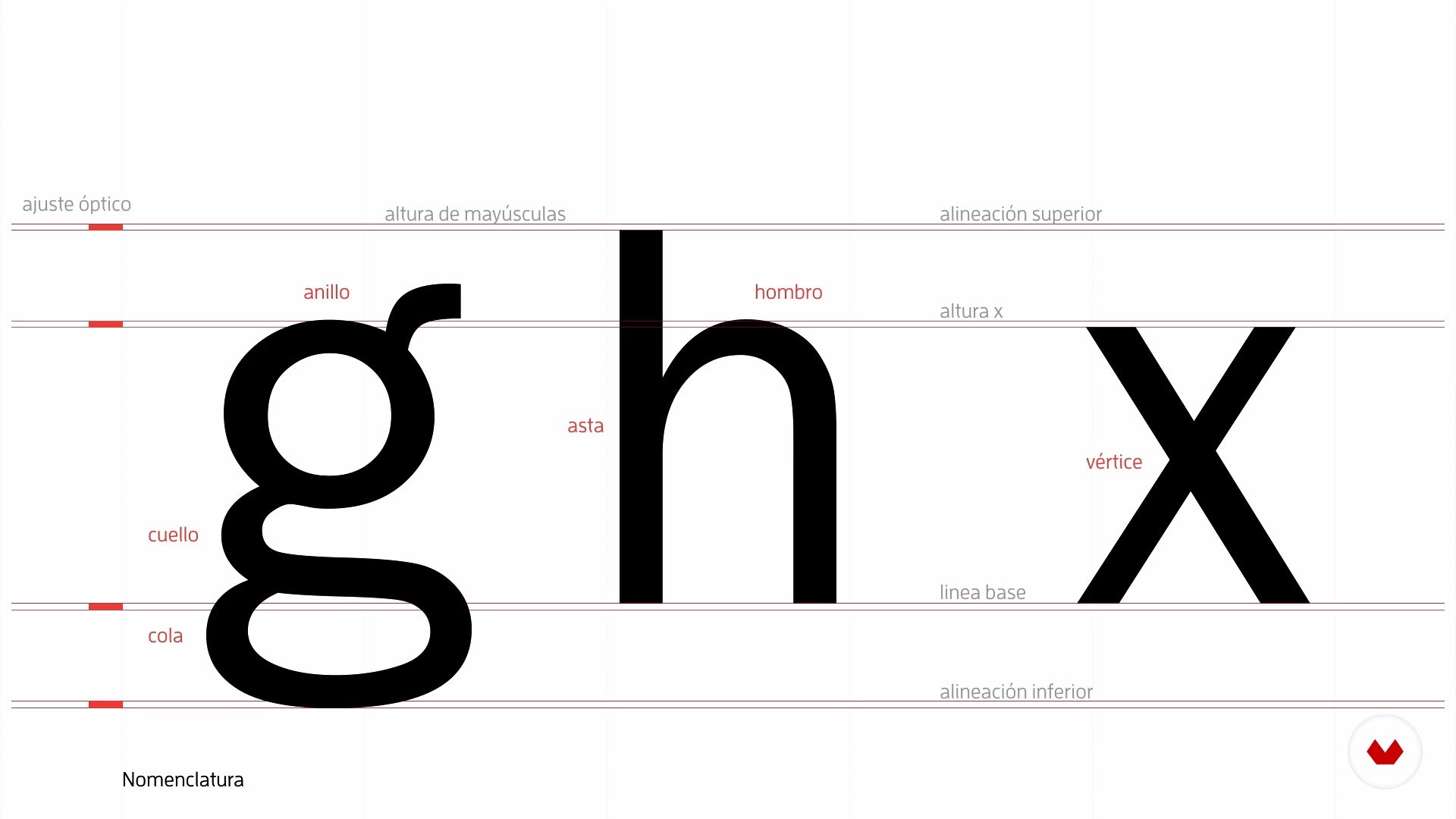
Conception d’affiches typographiques expérimentales
Attributs formels de la typographie
À propos de la leçon : Attributs formels de la typographie
“Dans cette leçon, nous examinerons certaines caractéristiques et attributs de base de la typographie à utiliser dans la conception d'affiche, tels que: nomenclature, forme, structure et proportion. ”
Dans cette leçon, BlueTypo aborde le sujet : Attributs formels de la typographie, qui fait partie du cours Domestika en ligne : Conception d’affiches typographiques expérimentales. Exprimez un concept créatif en mêlant les techniques numériques et traditionnelles.
“Pour définir la police dans le projet il est important de comprendre les attributs formels et expressif de la typographie. Ces attributs nous permettent de connaître les concepts de base de la typographie, comme la nomenclature, la structure, la forme et l'extension. Allons le voir. L'un d'eux est la nomenclature, c'est-à-dire que la police a une ligne de base et a une ligne qui est la hauteur de X. Cette hauteur de X correspond à la hauteur maximale du minuscule et cela permet de définir de nombreuses caractéristiques de la police que nous allons utiliser. Ensuite, nous avons l'alignement ...”